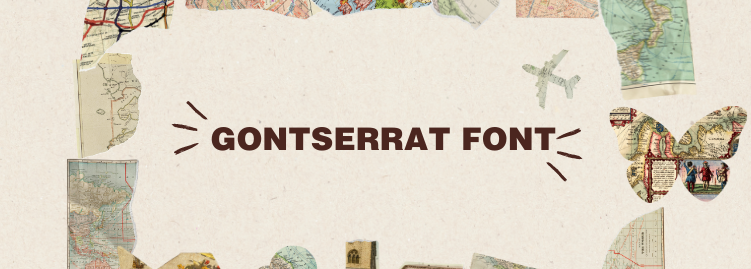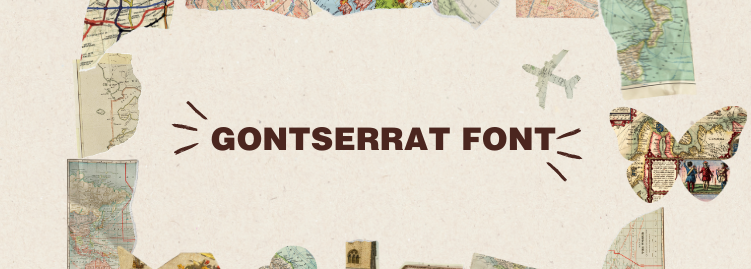
Gontserrat Font Free Download
Bạn đang cần tìm một font chữ hiện đại, thanh lịch và dễ đọc, thì Gontserrat Font thực sự là một sự lựa chọn hoàn hảo. Thuộc bộ font chữ không chân, Gontserrat Font mang đến sự sạch sẽ, rõ ràng và tinh tế cho các tài liệu soạn thảo. Các chữ cái được thiết kế với những đường nét vuông vức, góc cạnh, tạo cảm giác chắc chắn và chuyên nghiệp. Điều này, khiến văn bản trở nên vô cùng sắc nét, dễ đọc và dễ nhìn, đặc biệt hiệu quả trong các tài liệu như báo cáo, thiết kế trình chiếu hay các ấn phẩm số. Với những ưu điểm nổi bật, Gontserrat Font chính là một lựa chọn lý tưởng cho những ai muốn tạo nên những tài liệu soạn thảo hiện đại, chuyên nghiệp và dễ đọc.